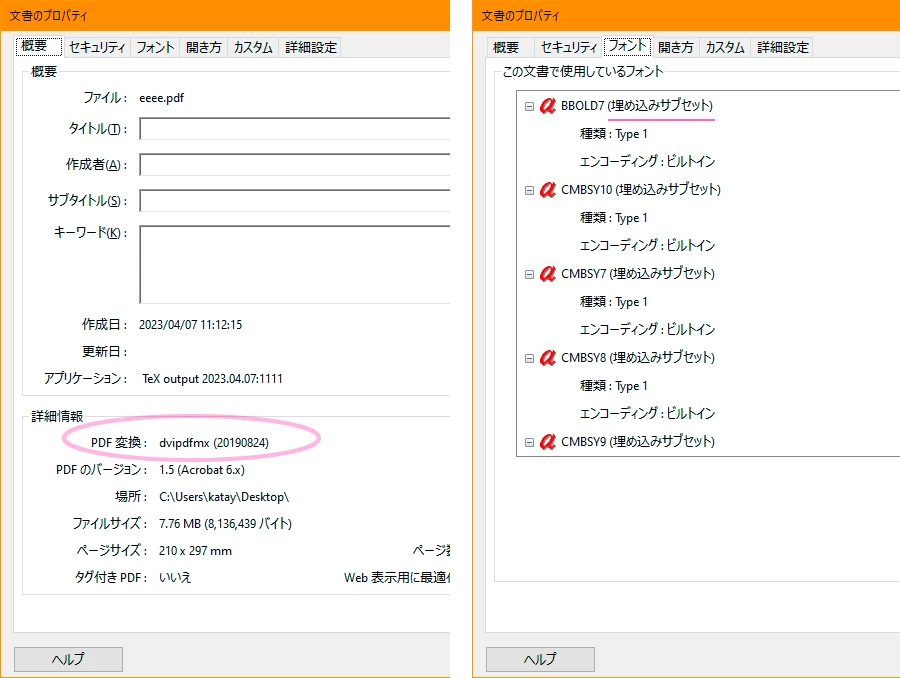
Microsoft EdgeでPDFを開くとフォントがおかしくなる
Microsoft EdgeでPDFを開くとフォントがおかしく(毛筆のように)なります
ファイルをPCにダウンロードしてAcrobatで開くと正常に(MS明朝などで)閲覧できます。
この件については、Microsoft Edgeで拡張機能を入れて一度は解決していたのですが、
最近また同様の現象が生じるようになりました。
もともとMicrosoft EdgeでPDFを閲覧する際に起きやすい現象ではあると思うのですが、直近のMicrosoft Edgeのバージョンアップで同様の現象が起こりやすくなった可能性はあるのでしょうか?
どうなのでしょう,どちらかというと最近のEdgeのほうがAcrobatと親和性が高そうな気がします。
あと,たまたま偶然に,フォントがおかしいPDFファイルに遭遇することが多いということはないでしょうか。偶然とは言い難い頻度でフォントがおかしくなりますか? EdgeでフォントがおかしくなるPDFファイルの文書プロパティを確認するなどして,何か特徴があれば提示してみてください。詳しい方から情報が得られるかもしれません。